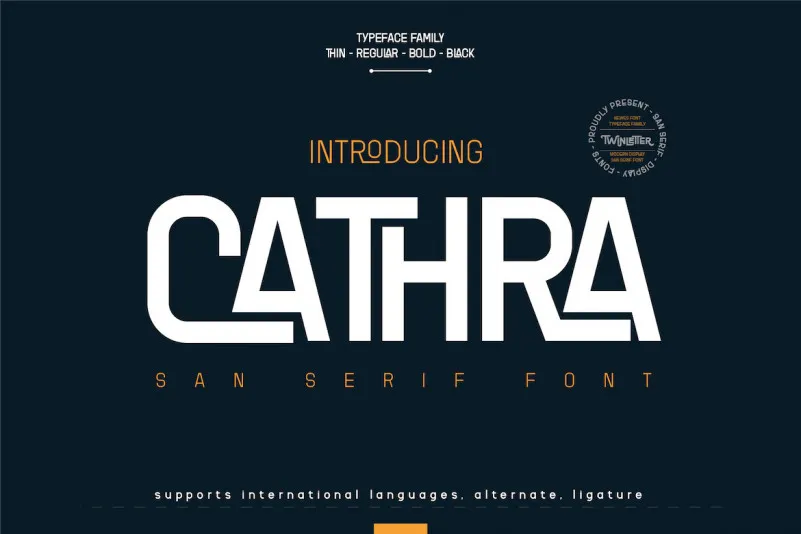
A Cathra Font é uma tipografia sans serif que se destaca por sua riqueza de recursos, especialmente para as necessidades de texto. Esta elegante fonte traz uma família de fontes variáveis, ideal para qualquer aplicação textual ou tipográfica. Além disso, ela incorpora ligações e alternativas específicas em algumas letras, proporcionando um toque delicado e refinado ao seu design. Com a Cathra Font, você pode explorar diferentes gráficos com uma variedade de estilos sem sair da página, tudo isso graças à sofisticada abordagem do designer twinletter na criação desta fonte. Não importa o uso que você dê para essa fonte, ela sempre irá se destacar por sua beleza e versatilidade em qualquer projeto gráfico.